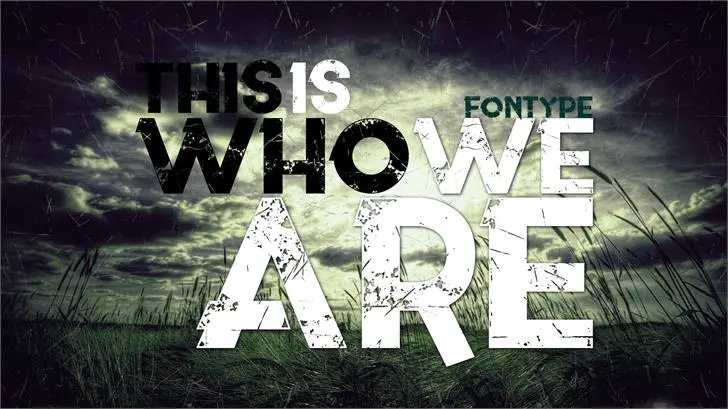
A This is who we are font é uma criação inovadora da LJ-Design Studios lançada em 2015. Esta elegante família de letras vem com diversas opções para adicionar um toque único e profissional a qualquer projeto gráfico. Com linhas finas e detalhes sutis, a This is who we are font se destaca como uma escolha perfeita para ambientes decorativos que desejam transmitir uma mensagem forte e pessoal. Ideal tanto para design de mídia digital quanto impressão em grandes tamanhos, essa fonte oferece um ar sofisticado sem perder o encanto natural. É a perfeição para quem busca um elemento distintivo em qualquer projeto de identidade visual ou design gráfico.